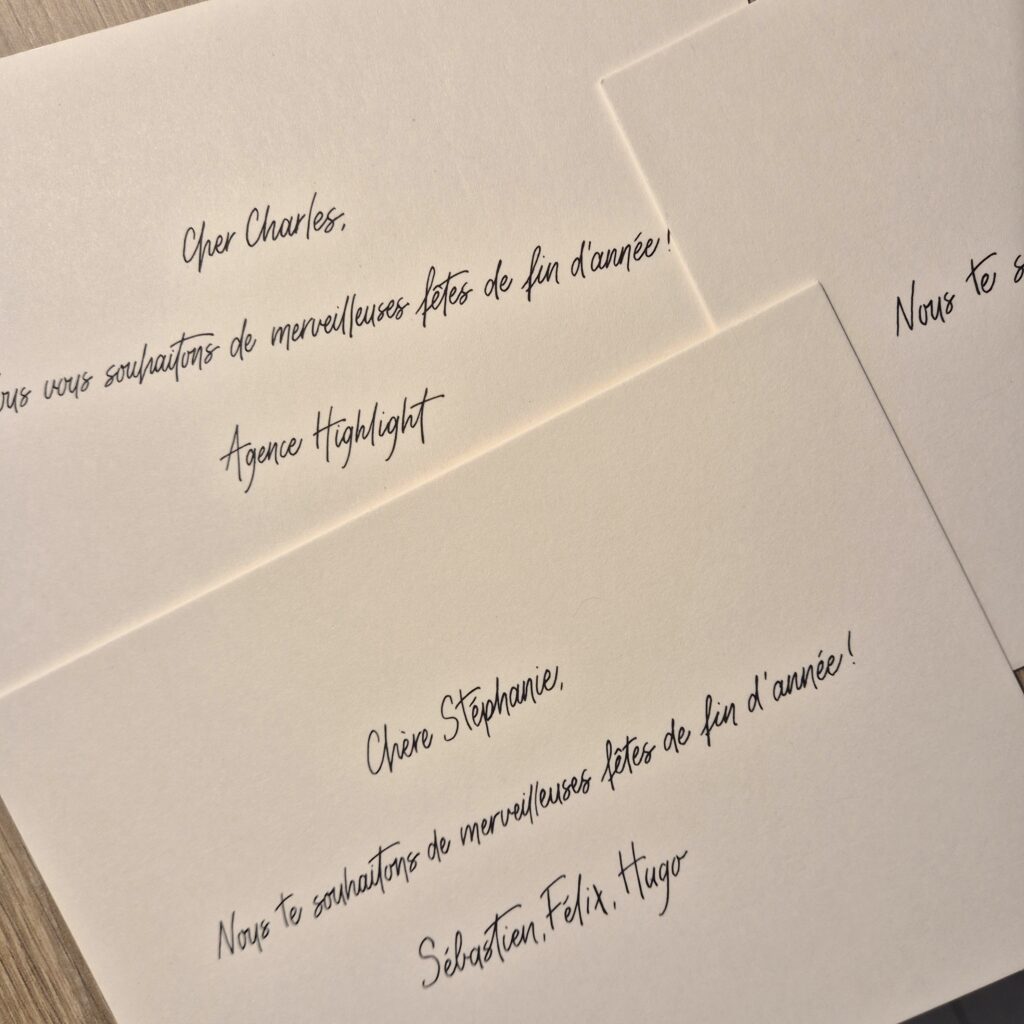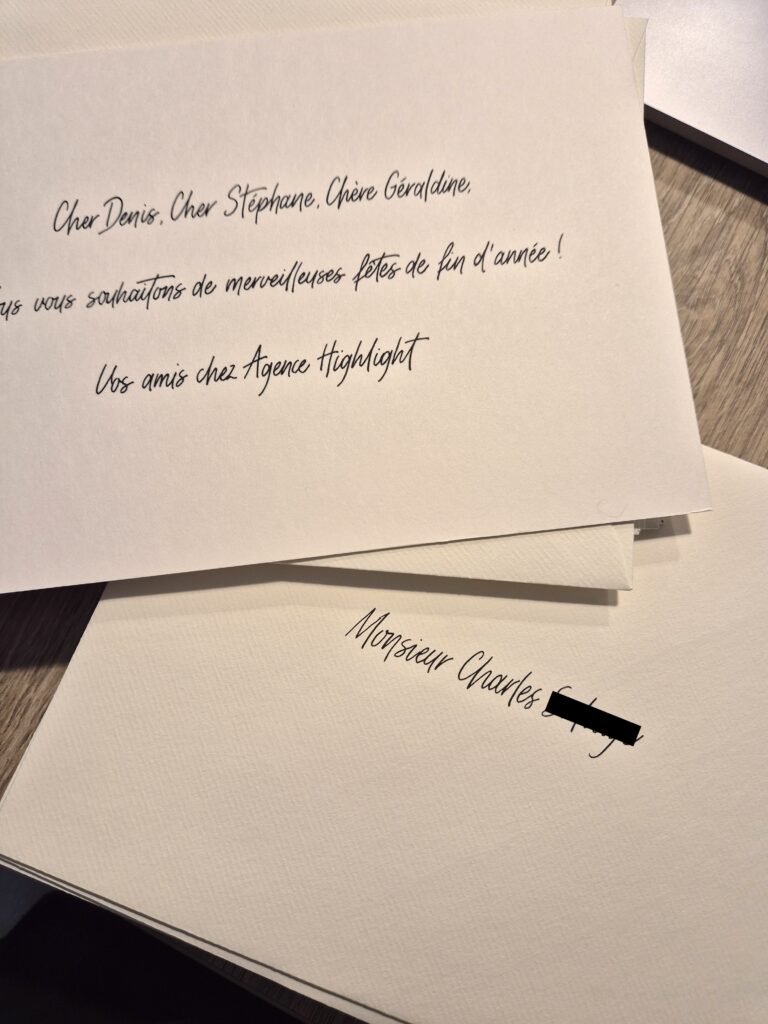
Agence Highlight
Personnalisation Carte de voeux 2025
Proposition et réalisation d’une vingtaine de carte de voeux pour l’année 2025 en calligraphie moderne à la plume sur papier cartonné 300gsm et enveloppes blanc ivoire.